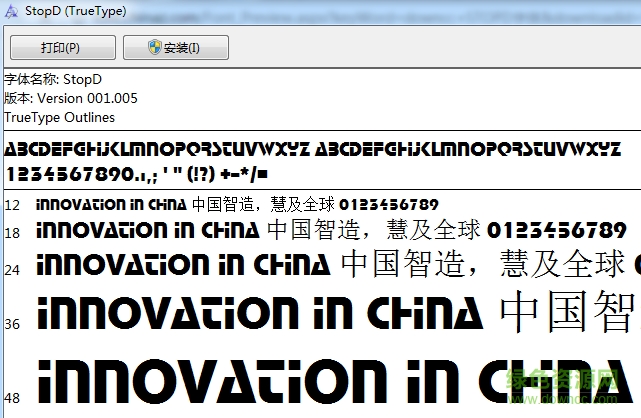
STOPD英文字體
STOPD字體是一款超好用的英文字體,字體擁有極強(qiáng)的個(gè)性,超粗狂的字型帶給用戶更佳的體驗(yàn)。有喜歡這款字體的朋友就趕快來(lái)綠色資源網(wǎng)下載使用吧!
stopd字體
STOPD字體是一款英文字體,該字體擁有十分全面的設(shè)計(jì)模板,讓用戶能夠享受更全面的個(gè)性字體,有需要的朋友就趕快來(lái)綠色資源網(wǎng)下載吧!